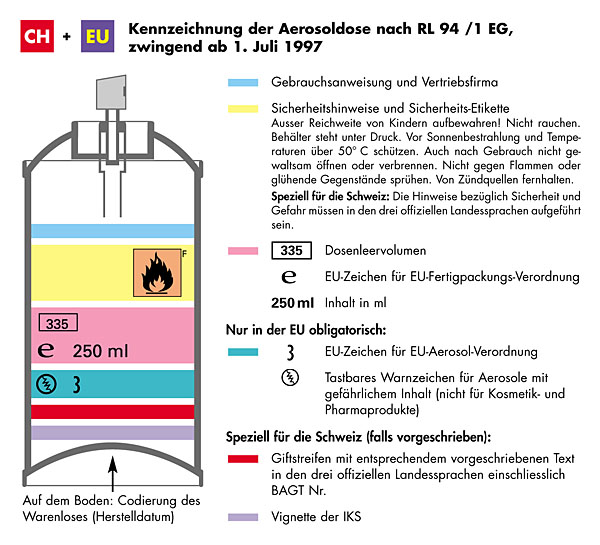
Zeichenname? Unbekanntes Symbol
ich suche die Bezeichnung eines mir unbekannten Zeichens/Symbols. Die Grafik zeigt den Zeil einer Mengenangabe auf einer Spraydose. Ich suche das Symbol ganz rechts. Sieht für mich aus wie eine gedrehte Drei. Ich weiß nur, dass es mit einer Druckgasverordnung zu tun hat, vermutlich ein Prüf- oder Normzeichen.
Ich will das Zeichen korrekt nachsetzen, benötige deshalb die Information; auch ob dieser in einer durchschnittlicher Opentype enthalten sein könnte.
Das ist eine ganz schnöde '3'. Ich weiß nicht, was sie bedeutet, aber ein Vergleich mit anderen Gasflaschen aus meinem Haushalt (Haushalts-Aerosol-Druckflaschen) zeigen ganz eindeutig, dass alle eine 3 aufweisen. Dabei scheint es egal zu sein, ob diese vor oder nach dem Kästchen auftritt; sie ist einfach da. Kann auch schon mal eine sehr 'technische' Drei sein, eine Ziffer ist es aber in jedem Falle - also auch in deiner oberen Abbildung...
ich hab noch einmal google bemüht und folgendes gefunden:
es scheint sich also doch um ein art symbol zu handeln. allerdings
hab ich auf diversen sprayflaschen auch die unterschiedlichsten
umsetzungen gefunden. irgendwo im netz stand "Das gespiegelte Epsilon,
das die Übereinstimmung der Packung mit den EU-Aerosol-Richtlinien
symbolisiert ..."
und da wundert man sich über den geschmack und hat die bestätigung doch seit jahren quasi vor augen...